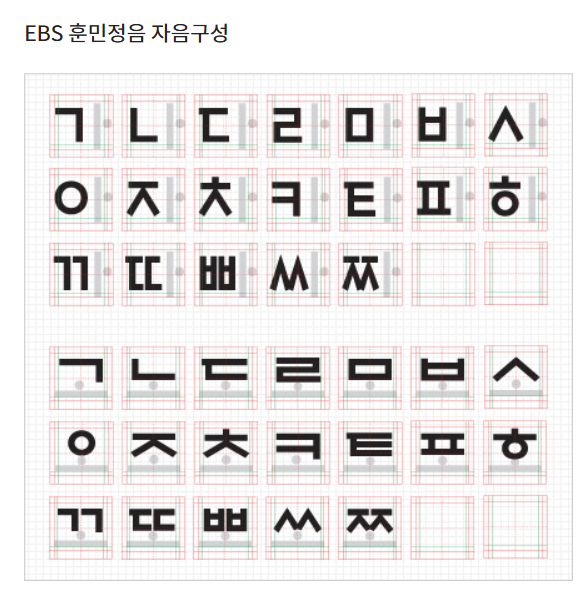
교육방송 EBS에서 제공하는 'EBS 훈민정음체'는 개인은 물론 기업에서도 활용할 수 있는 무료 폰트입니다. 독특한 디자인과 뛰어난 가독성 덕분에 블로그 썸네일, 유튜브 자막, 카드뉴스, PPT, 교육자료 등 다양한 곳에서 활용되고 있습니다.
EBS 훈민정음체란?
EBS 훈민정음체는 한글의 아름다움과 교육적인 이미지를 담아 제작된 공식 서체입니다.
기본적으로 깔끔한 고딕 계열이지만, 자음과 모음의 끝부분을 둥글게 표현하여 훈민정음의 느낌을 현대적으로 재해석한 것이 특징입니다.
특히 글자가 부드럽고 친근한 인상을 주기 때문에 교육 콘텐츠나 어린이 관련 디자인에서 활용도가 매우 높습니다.
EBS 훈민정음체 특징
- 깔끔하고 읽기 쉬운 고딕 스타일
- 훈민정음 감성을 현대적으로 표현
- 부드럽고 따뜻한 이미지
- 제목과 본문 모두 활용 가능
- 다양한 디자인 작업에 적합
또한 다음과 같은 굵기를 제공합니다.
- Light
- Regular
- Semi Bold
상황에 따라 원하는 굵기를 선택하여 사용할 수 있습니다.
특징이 강한 폰트는 대부분 타이틀(제목)에 활용이 높습니다.
특히 교육 관련 콘텐츠를 제작하는 분이라면 EBS의 브랜드 이미지와 잘 어울려 활용도가 높습니다.
EBS 훈민정음체는 무료이면서도 완성도가 높은 한글 서체입니다.